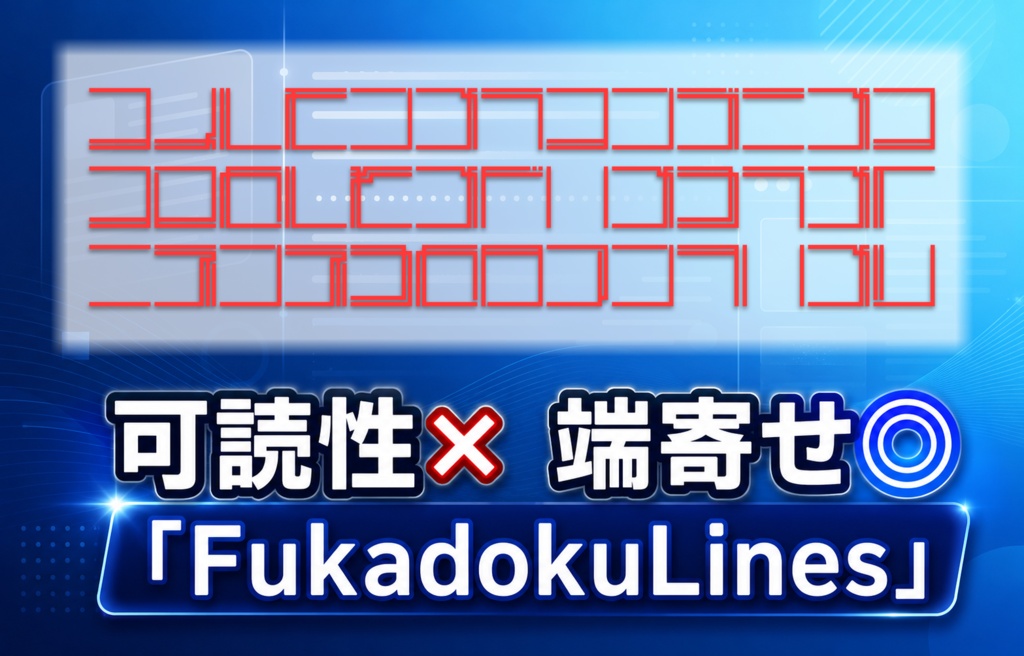
カタカナフォント「FukadokuLines」
端に寄りすぎて読めない!? 可読性無視のネタ系カタカナフォント! 個人・法人、商用・非商用問わずご利用いただけます。 ゲームのUI、動画のテロップ、同人誌、イラストなど、常識の範囲内で自由にお楽しみください。報告やクレジット表記も不要です(してくれると喜びます)。
収録文字について